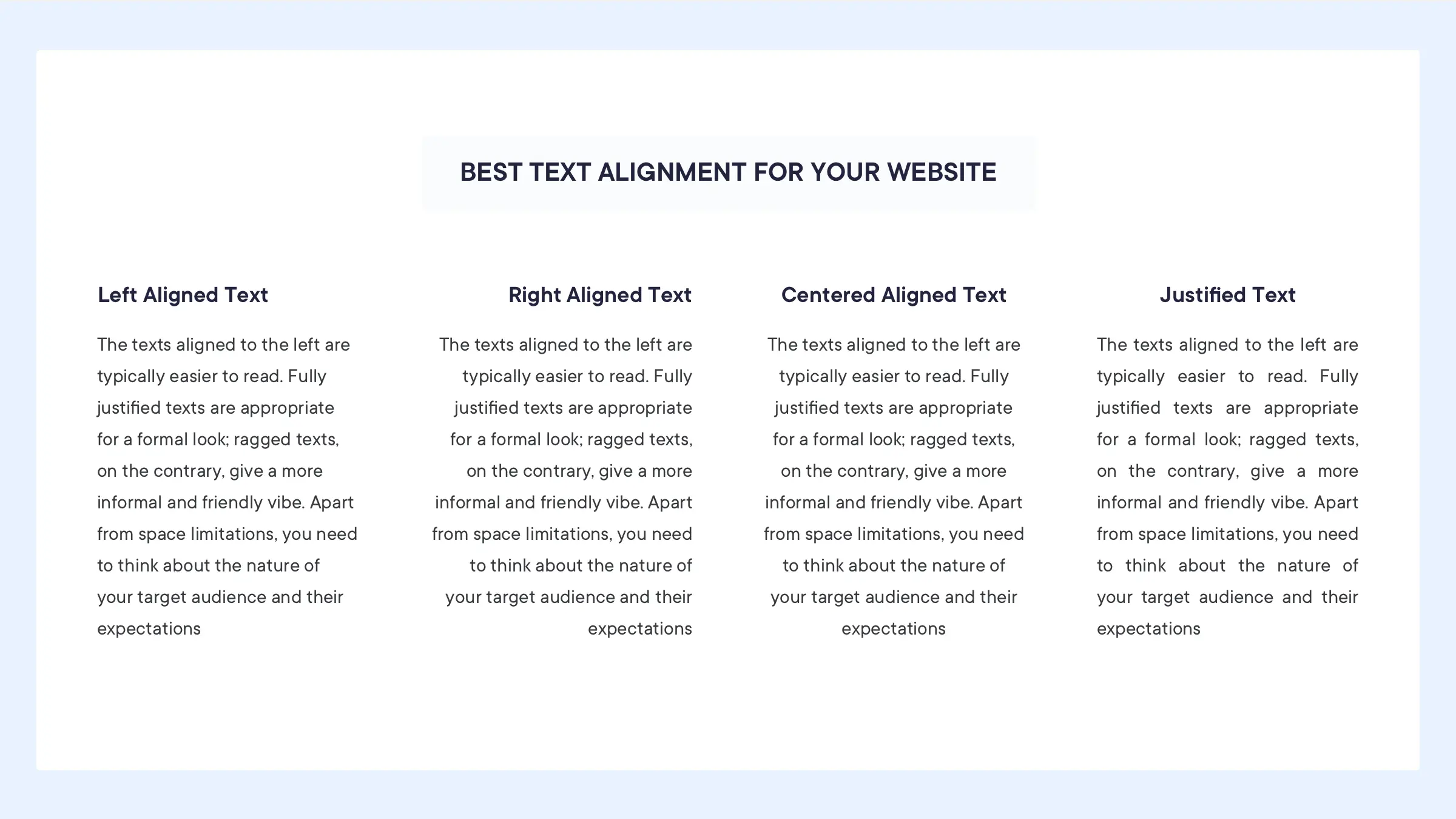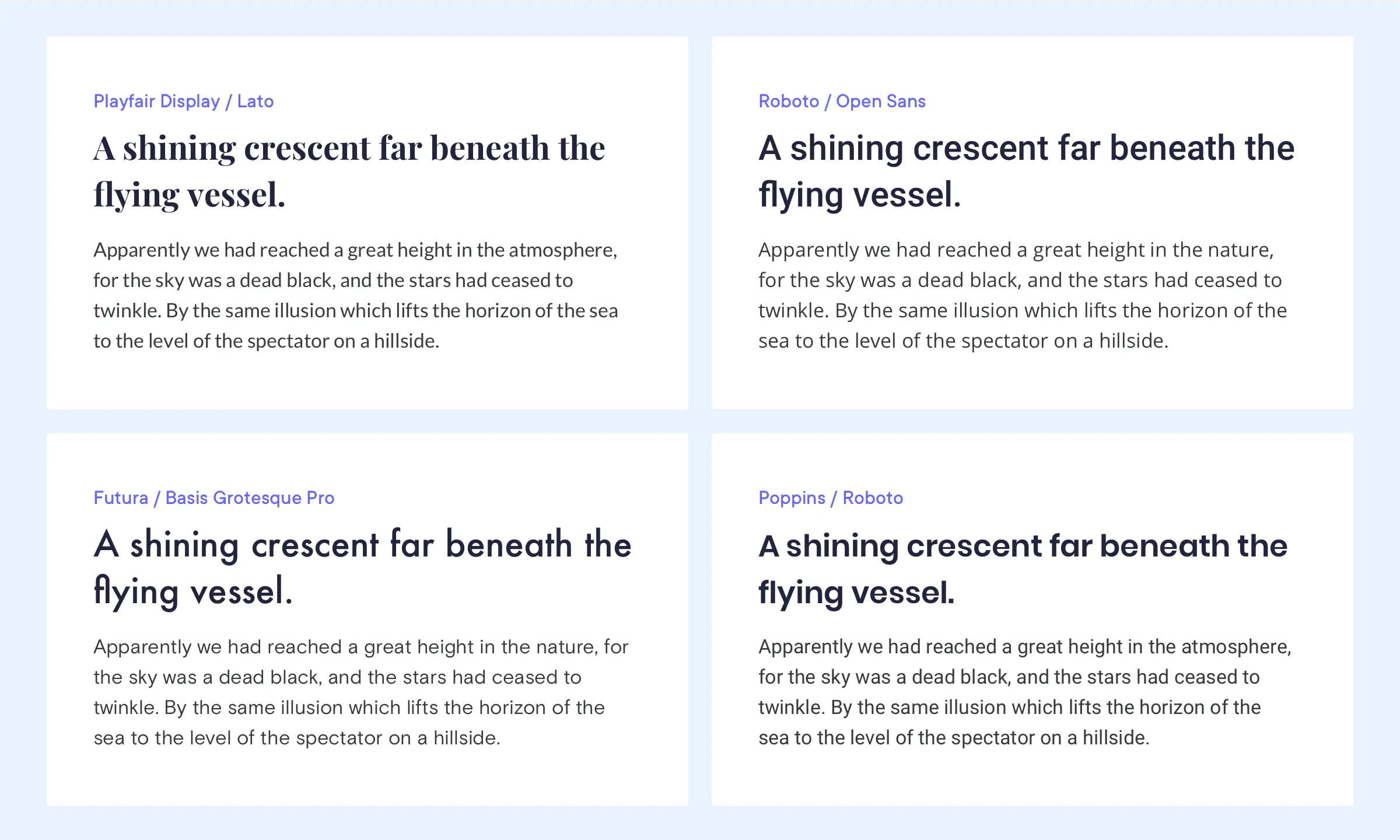
วิธีเลือกแบบอักษรที่ดีที่สุดสำหรับเว็บไซต์ WordPress ของคุณ
เผยแพร่แล้ว: 2020-03-01เมื่ออินเทอร์เน็ตเต็มไปด้วยเว็บไซต์ เป็นการยากที่จะคุยโวถึงความสำคัญของรายละเอียดทุกนาทีของการออกแบบเว็บไซต์ แม้จะมีการออกแบบที่สวยงามที่สุดเท่าที่จะจินตนาการได้ แต่เว็บไซต์หรือบล็อก WordPress ของคุณก็อาจไม่สมบูรณ์แบบ หากไม่มีฟอนต์ที่อ่านได้ ในทางตรงกันข้าม การจับคู่แบบอักษรที่เหมาะสม ขึ้นอยู่กับธุรกิจหรือเฉพาะกลุ่มของคุณ สามารถช่วยให้คุณดึงดูดผู้ชมและโดดเด่นจากคู่แข่งของคุณ
ในตอนแรก ให้ฉันบอกตรงๆ ว่าไม่ใช่เรื่องผิดปกติที่จะงงกับฟอนต์ WordPress หากคุณยังใหม่ในด้านการออกแบบเว็บ มีฟอนต์มากมาย และในฐานะมือใหม่หรือผู้ที่มีประสบการณ์น้อย อาจรู้สึกเหมือนเป็นเด็กที่ร้านขายขนม คุณสามารถผสมและจับคู่แบบอักษรได้ทุกประเภท และพยายามตัดสินใจตามความรู้สึกนึกคิดของคุณ แต่ในบางครั้งอาจไม่ได้ผลดีนัก บทความนี้มีจุดมุ่งหมายเพื่อช่วยคุณด้วยแนวทางปฏิบัติบางประการที่จะช่วยให้คุณมีเว็บไซต์ที่สะอาดตาและสวยงามยิ่งขึ้นด้วยการผสมผสานรูปแบบฟอนต์ต่างๆ ที่ลงตัว
แต่ก่อนที่เราจะเข้าสู่โดเมนของฟอนต์ เรามาพยายามทำความเข้าใจก่อนว่าฟอนต์มีบทบาทอย่างไรเมื่อเราออกแบบเว็บไซต์
มีฟอนต์ให้อ่าน ดังนั้นคุณควรนึกถึงเรื่องที่อ่านง่าย อย่างไรก็ตาม คุณอาจเลือกทำบางสิ่งที่อ่านไม่ได้โดยตั้งใจ หากคุณต้องการสร้างเว็บไซต์ที่มีรูปลักษณ์ที่เท่และสกปรก แต่ในกรณีส่วนใหญ่ ความสามารถในการอ่านควรเป็นประเด็นหลักเมื่อพูดถึงฟอนต์สำหรับเว็บไซต์
เมื่อเราจำกัดตัวเลือกของเราให้แคบลงในแง่ของความสามารถในการอ่าน ก็ถึงเวลาให้ความสำคัญกับสิ่งที่เราต้องการสื่อสารโดยใช้แบบอักษร แล้วกระบวนการของสิ่งนั้นเป็นอย่างไร? คุณต้องถามตัวเองสองสามคำถาม
อย่างแรกคือ – ต้องเป็นคลาสสิกหรือเก่าที่ชื่นชอบซึ่งได้รับการพิสูจน์แล้วหรือต้องใหม่? ให้ฉันอธิบายว่าทำไมฉันถึงคิดว่านี่เป็นคำถามที่สำคัญ แบบอักษรที่คุณเลือกต้องสะท้อนถึงวัตถุประสงค์ ผลิตภัณฑ์ หรือบริการของเว็บไซต์ของคุณ คุณอาจเลือกใช้แบบอักษรที่เป็นที่ยอมรับและเป็นที่รู้จัก หรืออาจเลือกแบบอักษรที่แปลกใหม่ ไม่มีอะไรผิดปกติกับสองวิธีนี้ แต่คุณต้องตัดสินใจตามเฉพาะเว็บไซต์ของคุณ
หากคุณกำลังกำหนดเป้าหมายธุรกิจ B2B หรืออุตสาหกรรมที่เกี่ยวข้องกับอสังหาริมทรัพย์และสถาบันการเงิน ควรใช้แบบอักษรที่เป็นที่รู้จักและเป็นที่ยอมรับ ในทางกลับกัน อาจเป็นการดีกว่าถ้าคุณเลือกอันใหม่และน่าสนใจ หากคุณต้องการโดดเด่นและสร้างความแตกต่างให้กับเว็บไซต์ของคุณจากคู่แข่งรายอื่น คุณต้องทำการตัดสินโดยขึ้นอยู่กับเป้าหมายของคุณ การทำความเข้าใจคำถามนี้จะนำคุณไปสู่ที่ที่คุณจะมองหาเมื่อคุณกำลังสำรวจแบบอักษร
หากฟอนต์ของคุณต้องเป็นแบบคลาสสิกและจดจำง่าย ฟอนต์นั้นหาได้ง่ายมาก คุณสามารถ google หรือดู บทความนี้ ซึ่งมีรายชื่อแบบอักษรคลาสสิก 25 แบบที่ใช้บ่อยที่สุด คุณสามารถเลือกแบบอักษรคลาสสิกแบบใดแบบหนึ่งหรือแบบผสมของแบบอักษรเหล่านั้น และยังคงสร้างเว็บไซต์ที่น่าตื่นตาตื่นใจได้ เนื่องจากสิ่งเหล่านี้ไม่เคยตกยุค
อีกอย่าง ถ้าคุณต้องการให้เว็บไซต์ของคุณดูใหม่และแตกต่าง คุณก็ควรเลือกใช้แบบอักษรที่ไม่ค่อยมีคนใช้ มีแหล่งข้อมูลออนไลน์มากมายที่คุณสามารถไปหาแบบอักษรใหม่ที่ได้รับการดูแลจัดการอย่างดีพอที่จะผ่านการทดสอบความสามารถในการอ่านได้ คุณสามารถหาแบบอักษรฟรีได้หากคุณมีงบประมาณจำกัด เราขอแนะนำให้ลอง ใช้ Google Fonts เพื่อดูตัวเลือกที่หลากหลาย หรือคุณสามารถเลือกใช้แบบอักษรพรีเมียมคุณภาพสูงได้ หากทางเลือกฟรีไม่เป็นไปตามที่คุณคาดหวัง
ต่อไปนี้คือสิ่งที่คุณต้องคำนึงถึงในขณะที่เลือกแบบอักษรที่เหมาะกับเว็บไซต์ WordPress ของคุณ
เริ่มต้นจากจุดเริ่มต้นกันเถอะ
เมื่อพูดถึงแบบอักษรของเว็บไซต์ มีหลายสิ่งที่ควรพิจารณาซึ่งอาจดูล้นหลามในตอนเริ่มต้น นั่นเป็นเหตุผลว่าทำไมจึงดีกว่าที่จะเริ่มต้นจากพื้นฐานก่อนที่จะดำเนินการต่อไป
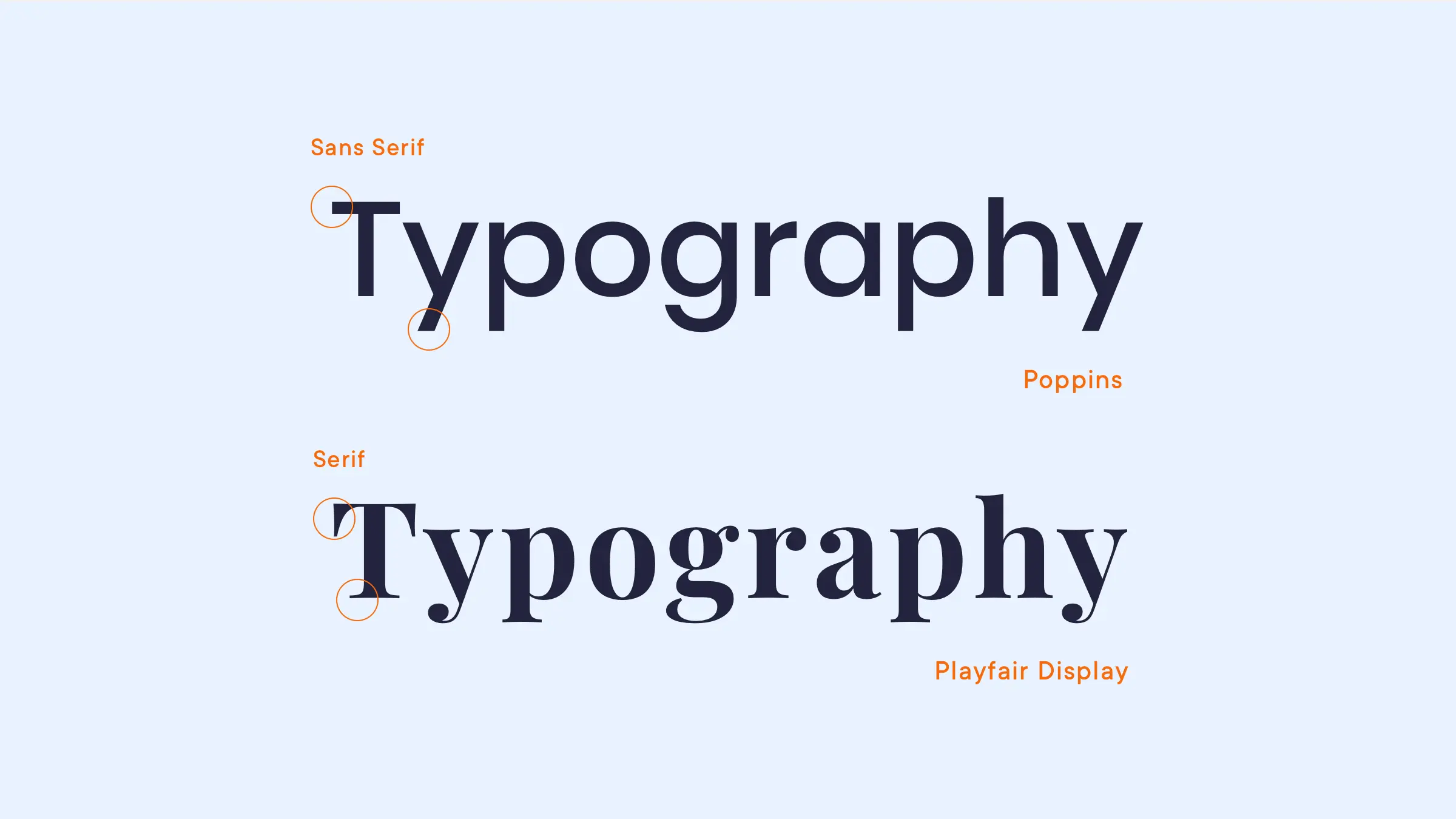
สิ่งที่ต้องเลือก – Serif หรือ Sans Serif?
เหล่านี้เป็นแบบอักษรหลักสองประเภท ใช่ มีแบบอักษรหลายร้อยแบบ แต่โดยทั่วไปแล้วจะจัดอยู่ในสองหมวดหมู่หลัก – Serif และ Sans Serif
แบบอักษร Serif มาพร้อมกับลายเส้นตกแต่งที่ส่วนท้ายของลายเส้นแนวตั้งและแนวนอนของตัวอักษร แบบอักษรที่จัดอยู่ในหมวดหมู่นี้เป็นทางเลือกดั้งเดิมที่สุด และยังถือว่าเป็นหนึ่งในรูปแบบแบบอักษรที่น่าเชื่อถือที่สุดอีกด้วย ฟอนต์ serif ยอดนิยมบางตัว ได้แก่ The Times New Roman, Georgia และ Baskerville คุณเลือกฟอนต์ WordPress ได้ไม่ผิดหรอก เช่น The Times New Roman เนื่องจากฟอนต์เหล่านี้อ่านง่ายสุด ๆ และมีมานานแล้ว
ในทางกลับกัน แบบอักษรของ Sans Serif มาพร้อมกับการออกแบบที่ทันสมัยและสะอาดตากว่าโดยไม่มีการตกแต่งหรือลายเส้นที่คมชัดบนตัวอักษร Helvetica, Futura และ Arial คือตัวอย่างบางส่วนของฟอนต์ Sans Serif ที่ใช้กันมากที่สุด
ประเภทของแบบอักษรที่คุณเลือกควรขึ้นอยู่กับผู้ชมเป้าหมายเป็นส่วนใหญ่ และอารมณ์ที่คุณต้องการทำให้เกิดผ่านเว็บไซต์ของคุณ โดยทั่วไปแล้วแบบอักษร Serif จะใช้เพื่อสร้างโทนที่เป็นทางการและสง่างามยิ่งขึ้น แม้ว่าแบบอักษรที่จัดอยู่ในหมวดหมู่นี้มักจะใช้ในนิตยสารและในอุตสาหกรรมแฟชั่นเพื่อสร้างรูปลักษณ์ทางเลือก
Sans Serif ขึ้นชื่อเรื่องความเรียบง่ายและความเรียบง่าย ฟอนต์ Sans Serif ยังมาพร้อมกับความยืดหยุ่นมหาศาลที่ให้คุณผสมผสานกับแบบอักษรแบบเก่าและสร้างบรรยากาศแบบเดิมๆ ได้ เว็บไซต์ส่วนใหญ่ในปัจจุบันชอบฟอนต์ Sans Serif เพื่อให้ดูสะอาดตาและทันสมัย
จับตาดู Kerning, Leading และ Tracking
นี่คือองค์ประกอบการออกแบบที่เกี่ยวข้องกับลักษณะโดยรวมของแบบอักษรของคุณ วิธีการเหล่านี้ถูกนำมาใช้เพื่อให้แน่ใจว่าข้อความที่น่าพึงพอใจและอ่านง่าย Kerning ใช้สำหรับช่องว่างระหว่างตัวอักษรสองตัว นำหน้าสำหรับช่องว่างระหว่างสองบรรทัด และการติดตามคือช่องว่างระหว่างกลุ่มของตัวอักษร
คำสุดท้าย
แม้จะมีการระเบิดขององค์ประกอบการออกแบบกราฟิกในโลกของการออกแบบเว็บ แต่มากกว่า 90% ของข้อมูลบนเว็บนั้นอยู่ในรูปแบบของการพิมพ์ สถิติแสดงให้เห็นว่าการเลือกแบบอักษร WordPress ที่ดีที่สุดสำหรับเว็บไซต์ของคุณมีความสำคัญเพียงใด ขั้นแรก ให้กำหนดวัตถุประสงค์ของเว็บไซต์ของคุณ จากนั้นจึงเริ่มเรียกดูชุดแบบอักษรที่ทำงานได้ดีกับสิ่งที่คุณกำลังจะวางบนไซต์ของคุณ แทบไม่มีข้อ จำกัด เมื่อพูดถึงจำนวนแบบอักษรหรือแบบอักษรบนเว็บ ดังนั้นคุณจะพบแบบอักษรที่เหมาะสำหรับเว็บไซต์ WordPress ของคุณอย่างแน่นอน